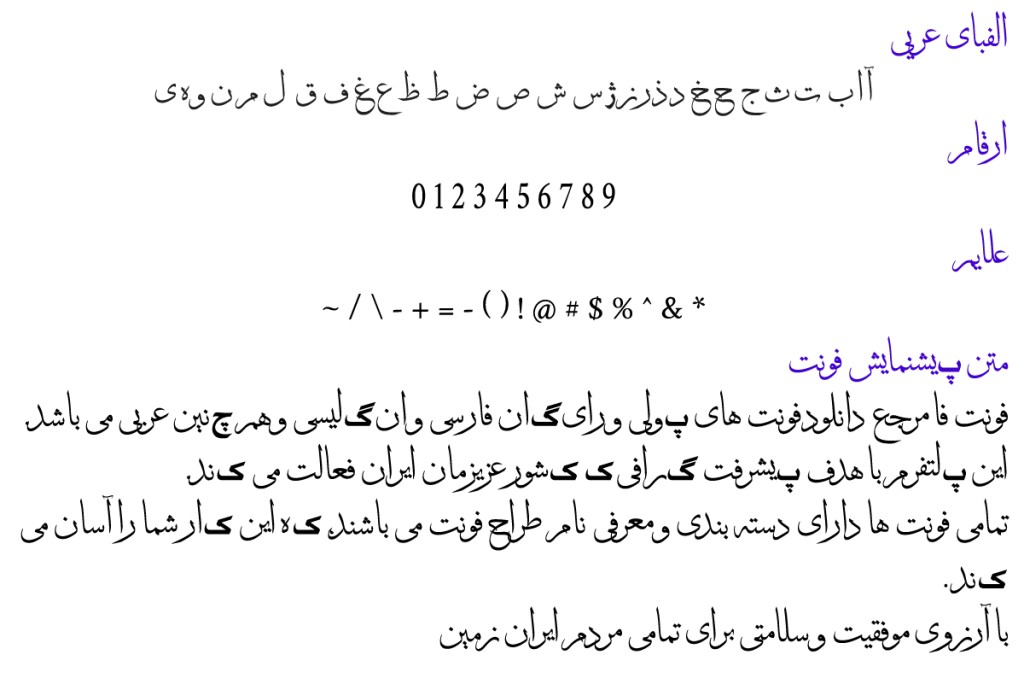
فونت عربی مشرف ثلث – A Moshref
نوع فونت: فونت خوشنویسی و فونت مذهبی
توضیحات و معرفی فونت مشرف ثلث
فونت عربی مشرف ( A Moshref Thulth ) از مجموعه فونت های آزاد می باشد، همینطور نوع فونت خوشنویسی و مذهبی می باشد.
این فونت زیبای عربی توسط علی مشرف طراحی و ایجاد شده است.